Scrivi una parola, scegli uno stile, scarica un PNG. Tutto qui, e ci vogliono circa dieci secondi.
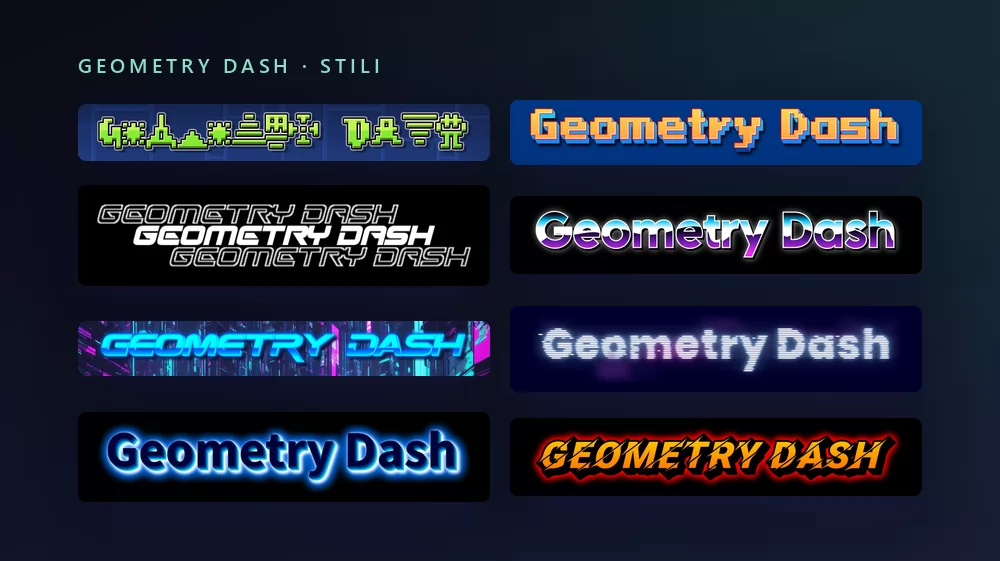
Vengono tutti dallo stesso generatore di font Geometry Dash, con uno stile diverso scelto dalla lista. Niente da installare, nessun account.
Informazioni sul font di Geometry Dash
Geometry Dash è un platform a ritmo uscito nel 2013 su iOS e Android, poi su Steam, sviluppato dallo svedese Robert Topala e pubblicato dalla sua società RobTop Games. Tocchi per far saltare un cubo tra le punte a tempo di musica, un colpo e ricominci, e l'editor di livelli lo ha trasformato in un gioco con milioni di livelli creati dai giocatori e un'intera scena YouTube intorno.
Due font fanno il lavoro, e "il font di Geometry Dash" può voler dire l'uno o l'altro. Il logo è composto in Oxygene 1, un font pixel di Jakob Fischer, il designer dietro Pizzadude. Il testo dentro il gioco, i nomi dei livelli, i menu, il logo RobTop, è molto vicino a Pusab, un carattere tondo e spesso della fonderia Flat-it. I giocatori che dicono "font GD" di solito intendono il secondo, perché è quello che vedono su ogni livello.
Come creare un testo Geometry Dash
Passo 1. Scrivi la parola
Apri il generatore e sostituisci il testo di esempio con il tuo: il nome di un livello, il nome di un canale, il titolo di un video, il tuo nome giocatore. Le lettere si ridisegnano mentre scrivi.
Passo 2. Scegli uno stile
Lo stile della pagina di destinazione costruisce ogni lettera con icone di livello sulla griglia blu dell'editor. È la cosa più Geometry Dash della lista, ed è la più difficile da leggere in piccolo, quindi per un nome o una miniatura passa allo stile pixel che corrisponde al logo. La scheda Stili permette di cambiare separatamente riempimento, contorno e ombra in entrambi.
Passo 3. Scegli il formato
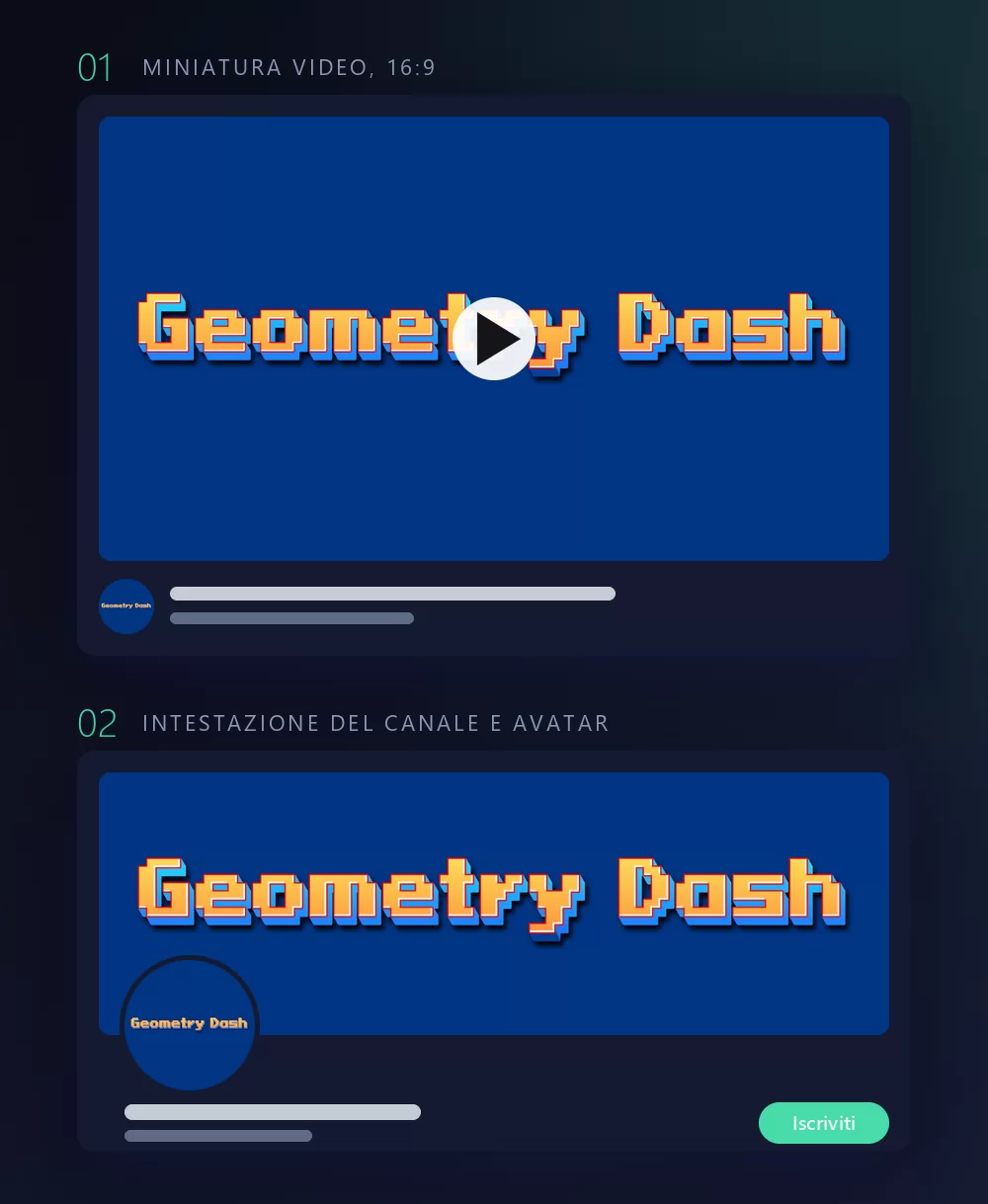
Imposta il formato prima di esportare e dopo non dovrai ritagliare niente. Un 16:9 per una miniatura video, un quadrato per un avatar o un'icona Discord, una striscia larga per l'intestazione di un canale. Le due simulazioni qui sopra sono ciò che diventano quei tre formati una volta al loro posto.
Passo 4. Scaricalo
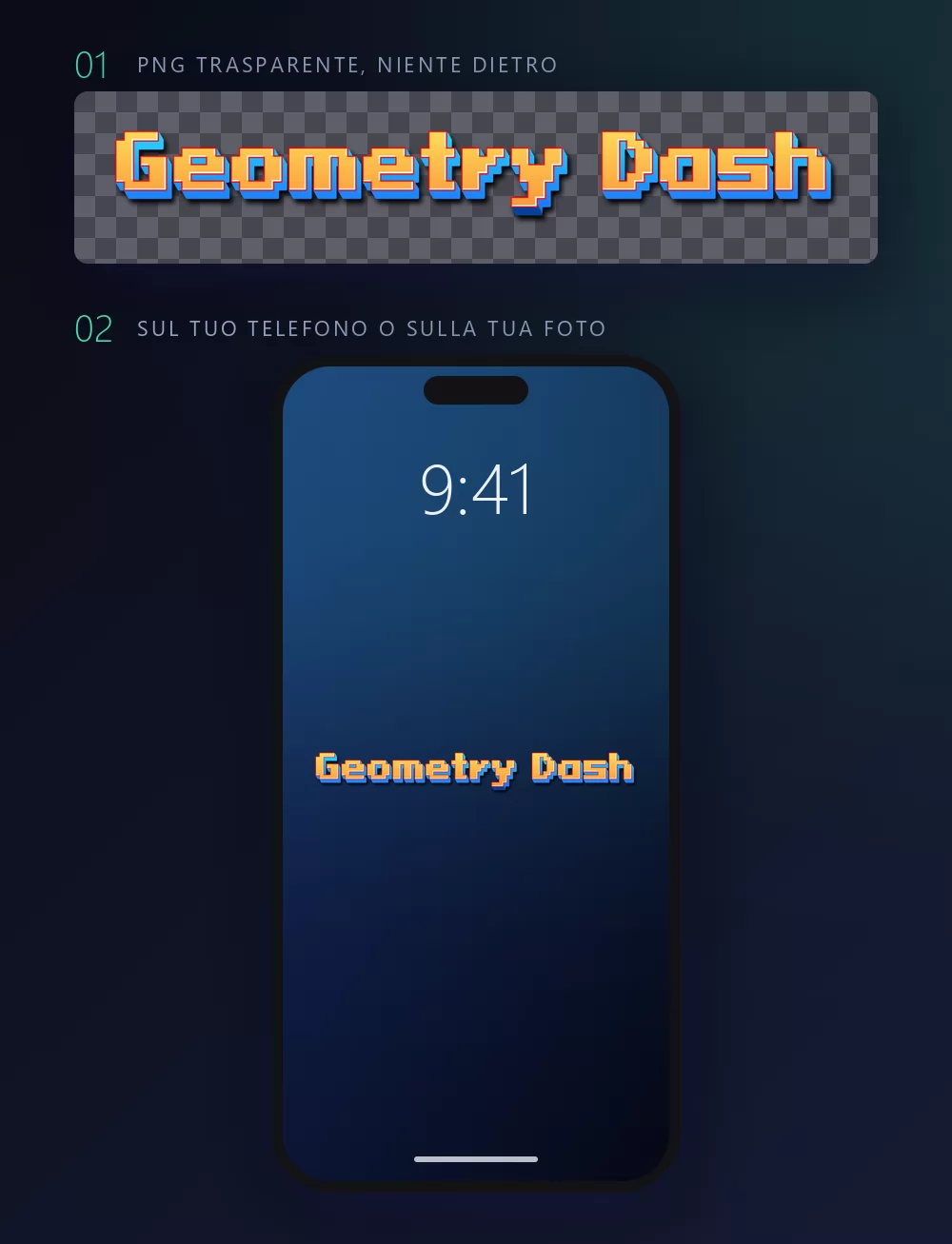
Nella scheda Scarica, prendi il PNG trasparente se vuoi mettere il titolo sul tuo screenshot. È l'opzione che quasi tutti si perdono, ed è quella che conta per la miniatura di un livello: il tuo screenshot del livello dietro, il titolo sopra, nessun riquadro blu intorno.
I nomi lunghi riempiono subito la larghezza
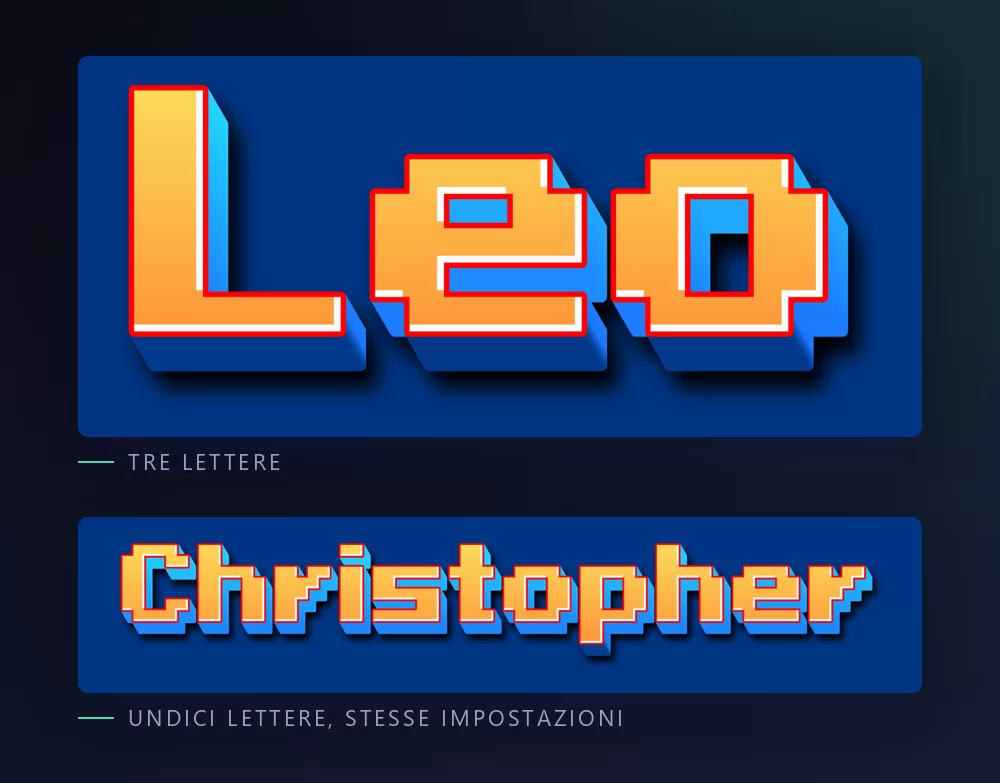
Più lettere ci sono, più si stringono. La spaziatura dei caratteri è un cursore della scheda Testo: aprila un po' e un nome lungo smette di sembrare schiacciato. La stessa scheda ha zoom, interlinea, curva e rotazione.
Lo stile del logo o lo stile dei livelli
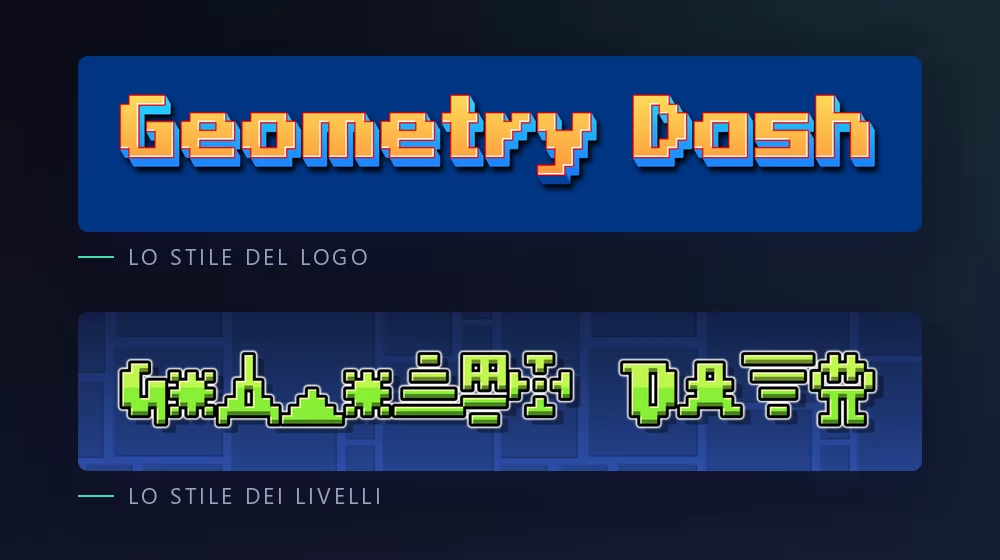
Lo stile del logo è il lettering pixel, l'Oxygene 1 della schermata del titolo: lettere squadrate con contorno scuro, arancione su blu. Si legge a qualsiasi dimensione, ed è per questo che è quello da usare per un nome.
Lo stile dei livelli è l'effetto di testo Geometry Dash stesso: ogni lettera assemblata con cubi, punte e portali sulla griglia dell'editor. Dice il gioco a colpo d'occhio e sta bene su una miniatura, non su una foto profilo che verrà rimpicciolita in un cerchio.
Quale font, se vuoi installarne uno
Pusab è il font del gioco, ed è quello che la gente cerca e non trova gratis. È un carattere commerciale di Flat-it, la fonderia di Ryoichi Tsunekawa, e si compra dalla fonderia o dai suoi rivenditori. Le copie che girano sui forum di GD e sui server Discord non sono licenziate.
Per l'aspetto di Pusab con una licenza pulita, le opzioni oneste sono i font tondi e spessi di Google Fonts: Luckiest Guy, il più vicino per peso e rimbalzo, Bowlby One di Vernon Adams, più pesante, e Titan One di Rodrigo Fuenzalida, un po' più stretto. Tutti e tre sono in licenza aperta, tutti e tre sono disponibili dentro Canva, e nessuno è Pusab. Ti danno la silhouette, che a dimensione di miniatura è quasi tutto ciò che l'occhio legge.
Cosa ci fa davvero la gente
Miniature di livelli per YouTube, prima di tutto: il nome del livello nel lettering del gioco sopra uno screenshot della parte più difficile. Poi banner di canale, avatar Discord e YouTube, schede profilo per i siti della community, sfondi del telefono e ogni tanto una maglietta stampata per un raduno. Quasi tutto funziona meglio con il PNG trasparente che con un font installato, perché l'aspetto sta nel contorno e nell'ombra quanto nelle lettere, e un file di font ti dà i contorni e nient'altro.
Come creare un testo Geometry Dash in Canva
Canva non ha né Pusab né Oxygene 1. Ha Luckiest Guy, Bowlby One e Titan One, quindi puoi ottenere l'aspetto spesso senza uscire. Per il logo pixel o lo stile dei livelli, crea le lettere come PNG trasparente e caricalo: entra direttamente in una miniatura Canva e resta nitido.
Posso usare lo stile Geometry Dash su cose che vendo? La licenza del font e il marchio sono due questioni separate. Geometry Dash appartiene a RobTop Games, quindi una licenza di font permissiva non coprirebbe comunque merce che sfrutta il gioco.
Perché il mio testo pixel è sfocato? L'antialiasing, o una scala che non è un multiplo intero. Disattiva la levigatura, tieni il font a una dimensione multipla della sua griglia di pixel, ed esporta alla dimensione finale invece di ridimensionare dopo.